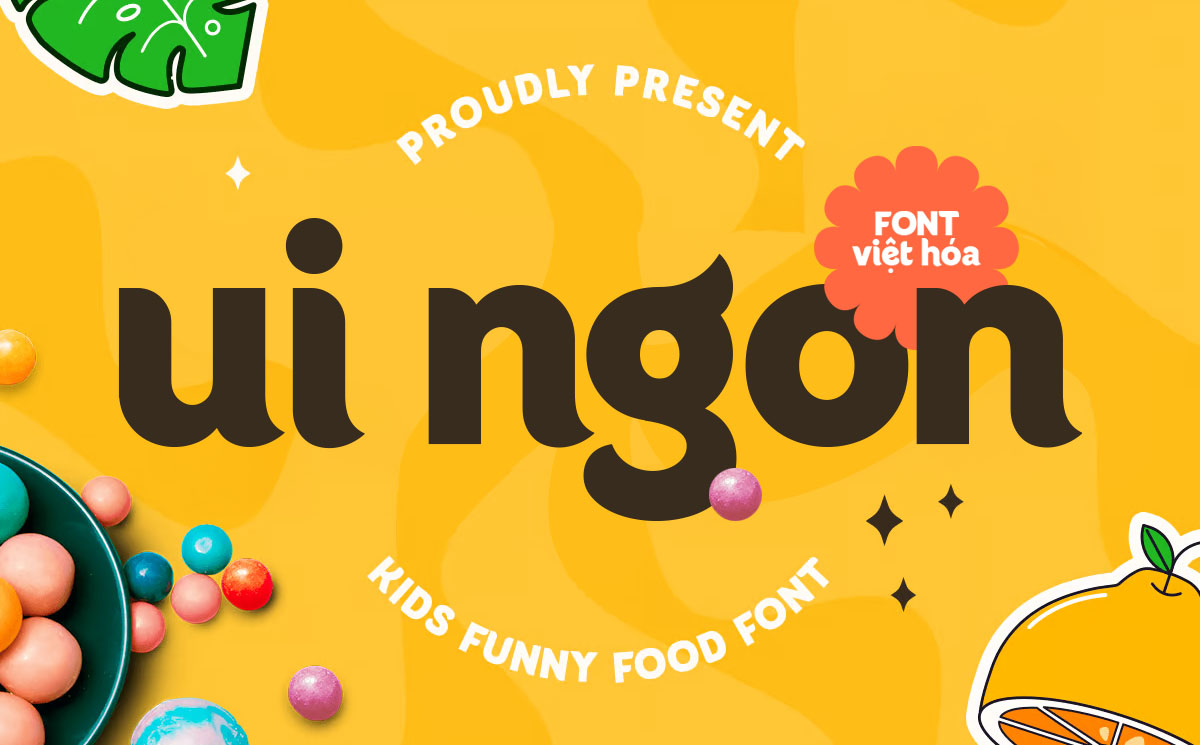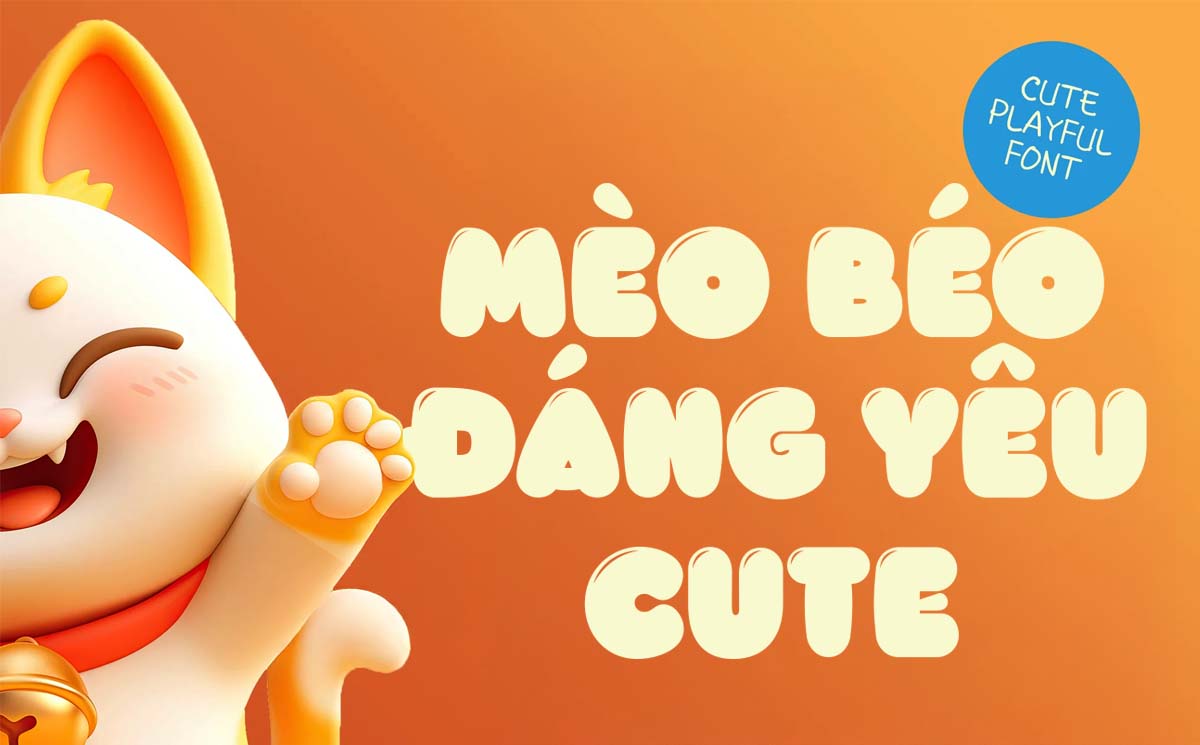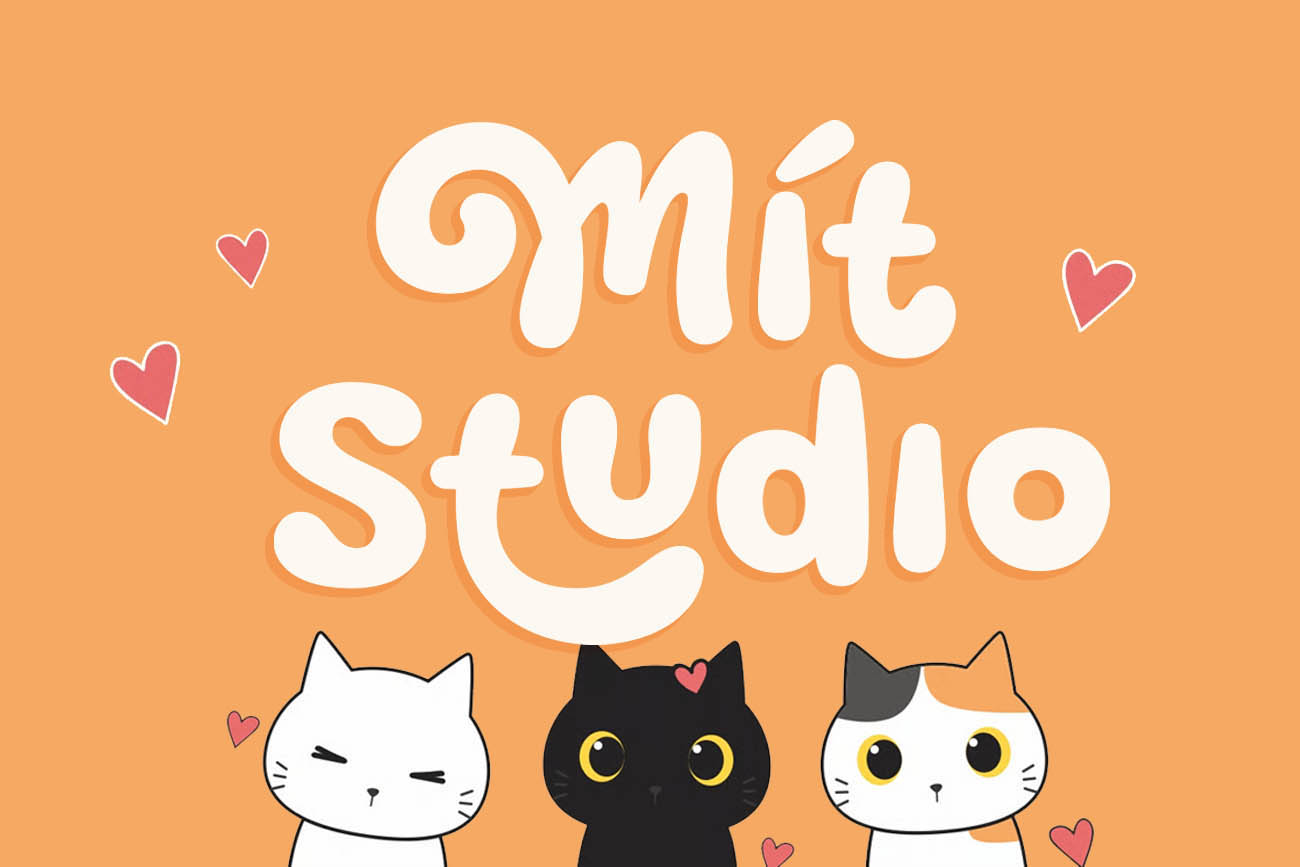
Top 20 font chữ cho trà sữa, quán nước, tiệm bánh và đồ uống take-away
Gợi ý 20 font trà sữa Việt hóa cho quán nước, tiệm bánh, menu đồ uống, ly nhựa, sticker topping và bao bì take-away.
Với trà sữa, quán nước, tiệm bánh và đồ uống take-away, font chữ là một phần rất lớn của cảm giác thương hiệu. Khách hàng nhìn menu, ly nhựa, sticker topping, hộp bánh, poster khuyến mãi và bài đăng social trước khi họ nếm sản phẩm. Một font đúng có thể làm món nhìn ngon hơn, vui hơn và dễ nhớ hơn.
Font trà sữa Việt hóa cần vừa cute, vừa rõ, vừa dùng tốt trên nhiều chất liệu. Chữ trên ly nhựa phải đọc được khi in một màu. Chữ trên menu phải rõ giá và topping. Chữ trên sticker hộp bánh phải đủ nổi bật dù kích thước nhỏ. Vì vậy, không phải font nào đáng yêu cũng phù hợp để dùng toàn bộ hệ thống.
Bài viết này tổng hợp 20 font TH Việt hóa phù hợp cho trà sữa, quán nước, tiệm bánh, menu đồ uống và bao bì take-away. Mỗi font có gợi ý ứng dụng cụ thể, ảnh preview và link tải để bạn chọn nhanh theo phong cách thương hiệu.
Font trà sữa và tiệm bánh cần đáp ứng điều gì?
Đầu tiên là cảm giác ngon mắt. Các ngành đồ uống và bánh ngọt thường cần chữ bo tròn, mềm, vui hoặc handmade để gợi vị ngọt, topping, kem, sữa, trái cây và sự thân thiện. Font quá cứng có thể làm thương hiệu mất đi sự gần gũi.
Thứ hai là độ đọc trên menu. Một menu trà sữa có rất nhiều dòng: size, topping, phần trăm đường, đá, giá, combo, món mới. Nếu font quá trang trí, khách sẽ khó đọc và nhân viên cũng dễ bị hỏi lại.
Thứ ba là khả năng dùng trên bao bì. Logo và slogan trên ly nhựa, tem dán, hộp giấy hoặc túi take-away thường bị giới hạn kích thước. Font nên có hình dáng rõ, không quá mảnh và không bị mất dấu tiếng Việt khi in.
Tiêu chí chọn font cho quán nước, menu đồ uống và bao bì ly nhựa
Chọn font theo vai trò, không dùng một font cho tất cả
Một font cute có thể rất đẹp cho tên món, nhưng chưa chắc phù hợp cho giá, ghi chú size hoặc mô tả topping. Hệ font tốt thường gồm một font headline nổi bật, một font phụ dễ đọc và một font nhấn cho sticker hoặc lời nhắn.
Kiểm tra dấu tiếng Việt với tên món thật
Hãy thử các cụm như “trà sữa trân châu”, “kem cheese”, “sữa tươi đường đen”, “bánh flan”, “trà đào cam sả”, “đá xay matcha”. Nếu dấu bị sát hoặc chữ khó đọc khi thu nhỏ, font không nên dùng cho menu chính.
Test trên màu thương hiệu và chất liệu in
Font đẹp trên nền trắng có thể yếu trên ly trong, nền pastel hoặc ảnh đồ uống nhiều màu. Trước khi in hàng loạt, hãy thử trên mockup ly, sticker, hộp bánh và menu treo quầy để chắc rằng chữ vẫn nổi bật.
Top 20 font TH Việt hóa cho trà sữa, quán nước, tiệm bánh và take-away
Danh sách dưới đây thiên về nhóm font cute, hoạt hình, bo tròn và viết tay thân thiện. Đây là các nhóm font dễ tạo cảm giác ngọt, vui, trẻ trung và hợp với thị trường đồ uống take-away.
1. TH Bagyo Sans
Phù hợp cho: menu trà sữa, logo quán nước, sticker topping, ly nhựa.
TH Bagyo Sans có dáng bo tròn vui nhộn, rất hợp với các thương hiệu trà sữa trẻ trung. Font đủ dễ thương để dùng trên ly nhựa, sticker topping, menu món mới và poster combo. Khi dùng cho menu dài, hãy để font ở tiêu đề hoặc nhóm món, còn giá và mô tả nên dùng font phụ gọn hơn.
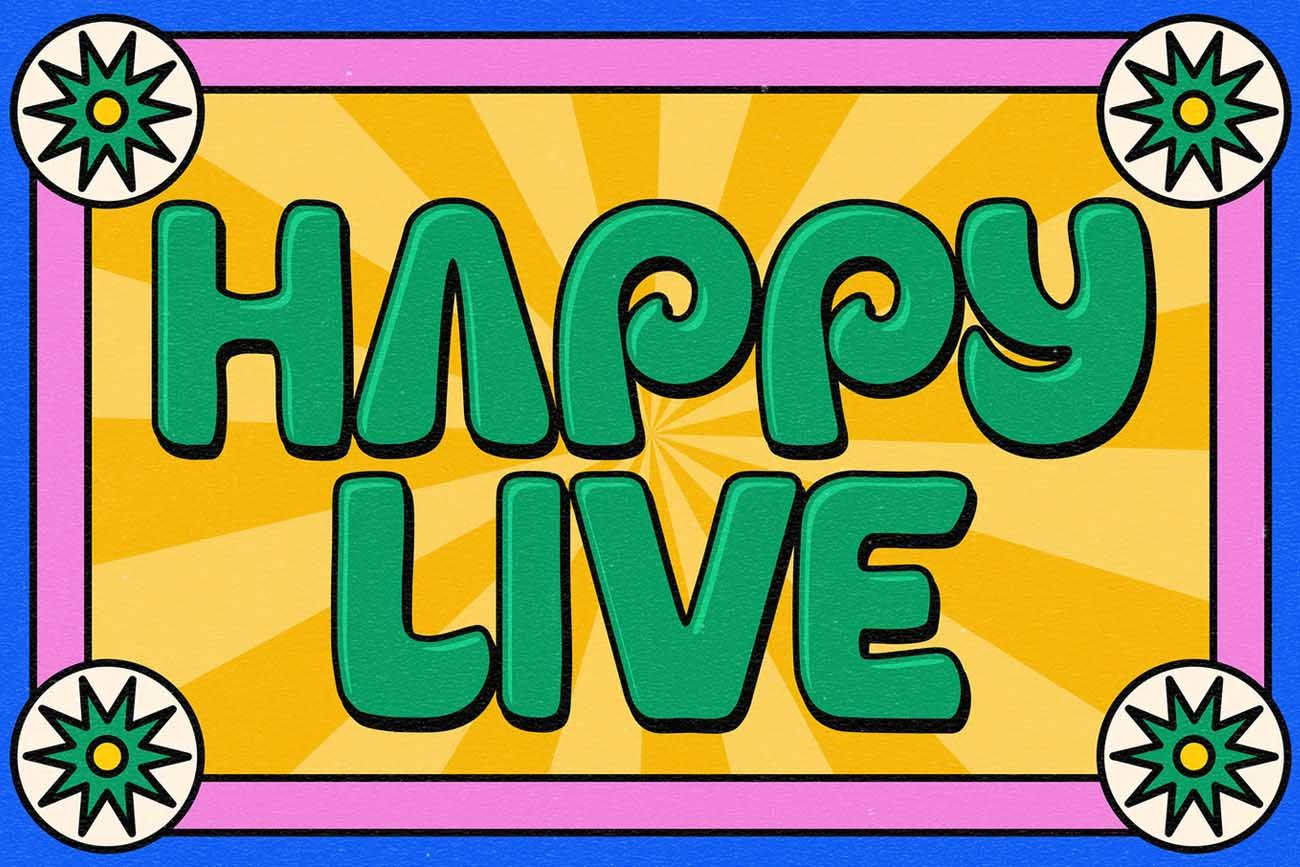
2. TH More Sugar
Phù hợp cho: trà sữa ngọt, tiệm bánh cute, poster topping, combo dessert.
TH More Sugar đúng tinh thần ngọt ngào, vui và dễ nhớ. Font hợp với các tên món như trà sữa kem cheese, bánh flan, pudding, milk foam hoặc dòng sản phẩm theo mùa. Với các thiết kế cần cảm giác “ngon mắt”, More Sugar giúp headline nổi bật ngay từ xa.
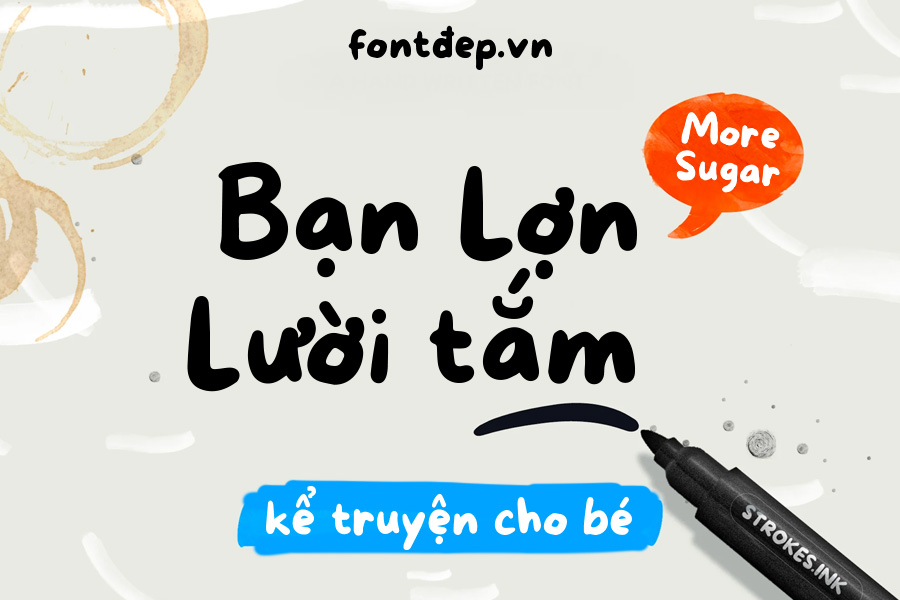
3. TH Playful Bubble
Phù hợp cho: logo trà sữa, nhãn ly, poster khai trương, menu trẻ trung.
TH Playful Bubble có nét bong bóng vui, phù hợp với quán nước hướng đến học sinh, sinh viên và khách trẻ. Font tạo cảm giác mềm, đầy đặn và nổi bật trên nền màu pastel. Nên dùng font cho tiêu đề lớn, tên món signature hoặc nhãn topping thay vì toàn bộ menu.
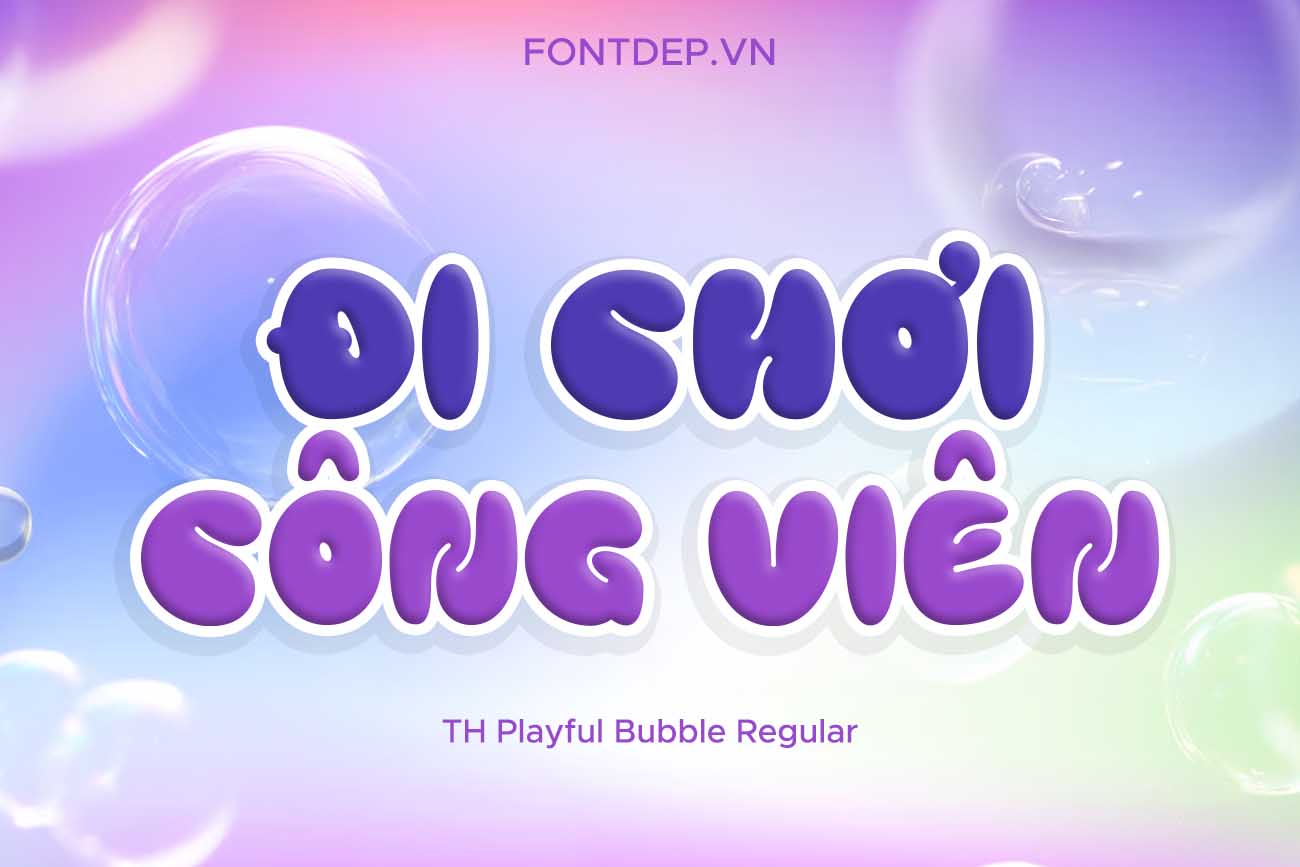
4. TH Cherry Feeling
Phù hợp cho: tiệm bánh handmade, sticker cảm ơn, menu dessert, packaging nhỏ.
TH Cherry Feeling là font viết tay dễ thương, hợp với các tiệm bánh, trà trái cây, quán nước handmade hoặc bao bì cần cảm giác thân thiện. Font đẹp ở các dòng ngắn như “fresh daily”, “made with love”, “bánh mới ra lò” hoặc lời nhắn trên sticker dán hộp.
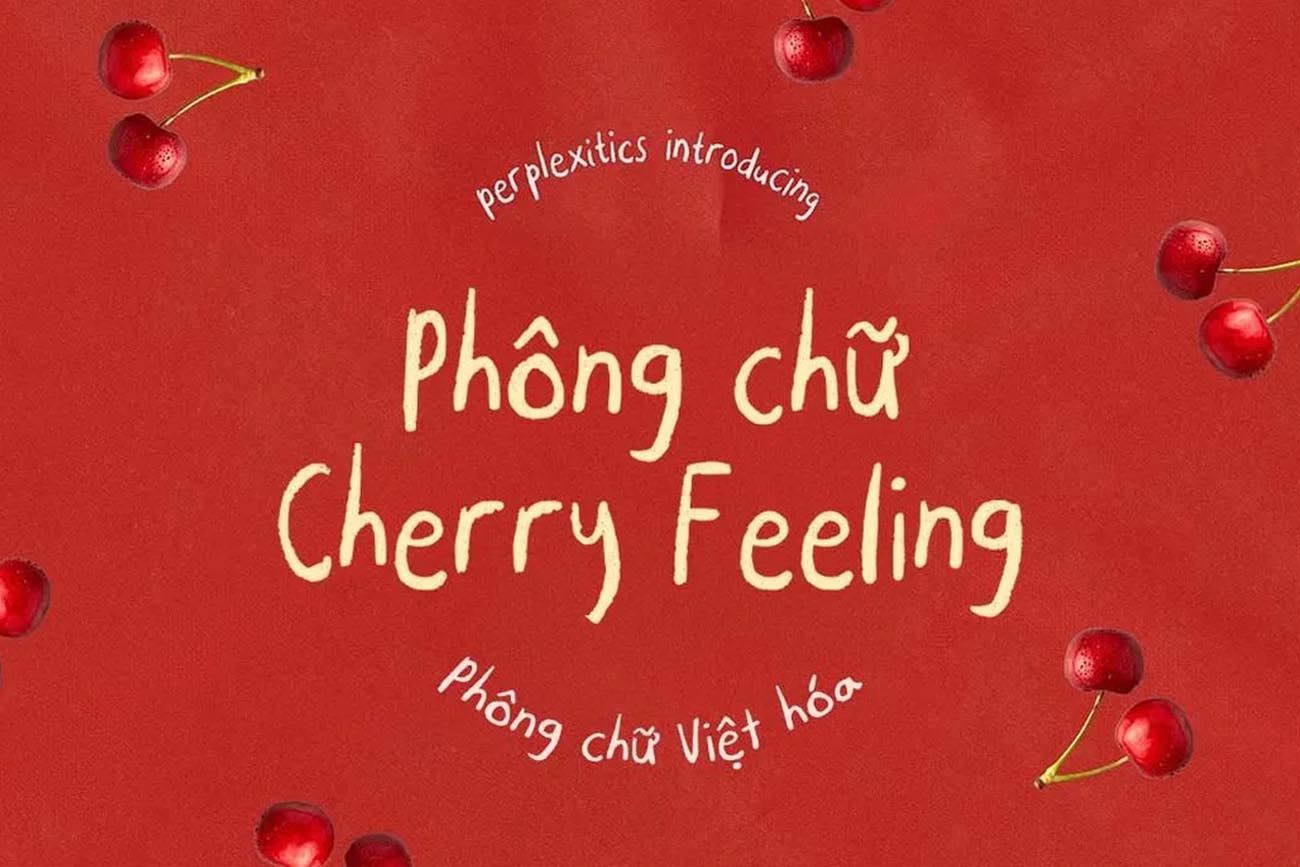
5. TH Glafty
Phù hợp cho: brand trà sữa năng động, quán nước take-away, campaign social.
TH Glafty mang cảm giác vui tươi, năng động và hiện đại. Font phù hợp với quán nước có màu sắc mạnh, nhiều món theo trend hoặc chiến dịch social media liên tục. Bạn có thể dùng Glafty cho headline poster, tên món mới, banner ưu đãi và các thiết kế cần năng lượng trẻ.
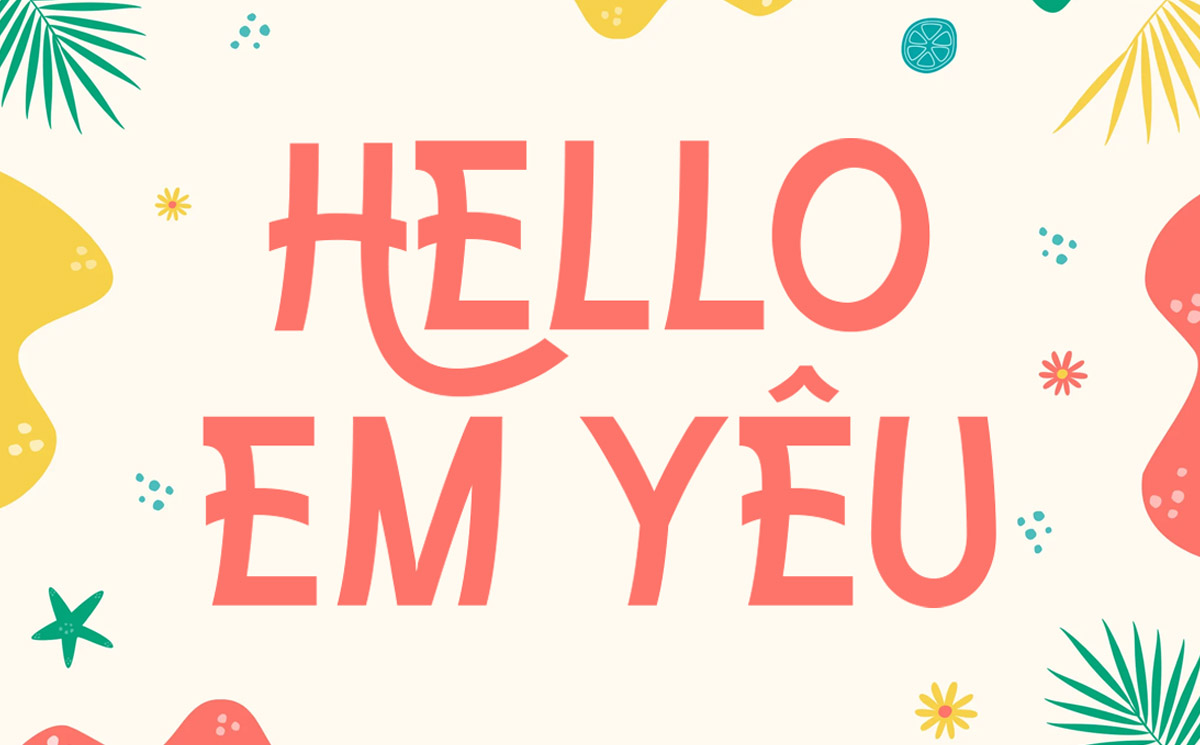
6. TH Mighty Kingdom
Phù hợp cho: tiệm bánh, kem, đồ uống ngọt, nhãn sản phẩm cute.
Font trà sữa Việt hóa đẹp nên tạo cảm giác ngon, vui và dễ nhớ, nhưng vẫn phải đọc rõ trên menu và bao bì. Hãy chọn font theo vai trò: font headline cho tên món, font phụ cho giá và mô tả, font viết tay cho lời nhắn hoặc sticker.
Nếu cần font cho trà sữa, quán nước, tiệm bánh và đồ uống take-away, bạn có thể bắt đầu với TH Bagyo Sans, TH More Sugar, TH Playful Bubble, TH Super Dessert, TH Cartoon 5, TH Choco Fantine hoặc TH Sophia Melanie. Tải font, test với tên món thật và in thử trên ly hoặc sticker trước khi triển khai hàng loạt.